三月九日, 香港字體設計師許瀚文(Julius)在網上眾籌平台發起兩個月的「空明朝體」專案結束,取得空前成功,獲近五千人投資,一共募集得約二千五十萬台幣(約五百六十萬港元)。這筆資金足以支持許瀚文的團隊以一年時間,完成一套全新明體字。
「空明朝體」是許瀚文在二○一四年的構想。當時,他在想像創造一套柔韌秀麗,易讀且符合漢字美學的新字體,意圖革新枯燥單調的中文閱讀感受。六年間,他研究實驗,幾經調整,如今夢想逐步成真。許瀚文喜憂參半,「知道有這麼多人真心支持時,更加不可以衰。」他緊張但不敢怠慢,「唔掂都要掂,無得話唔掂,我哋都有信心。」
夢想成真以後
眾籌期完結,許瀚文及其兩位團隊成員、資深造字匠人張堅強和馮景祥隨即展開「空明朝體」的開發。現在,張馮兩位師傅每星期需要造好合共二百個中文字。如一切按計劃進行,來年三月,「空明朝體」基本款七千六百字就可供下載,其後在七月推出完整版。
起初,許瀚文以為自己和兩位師傅在蒙納香港分公司有共事經驗,是次合作生產「空明朝體」也能順利,豈料到真正造字,才發現磨合需時,加上「空明朝體」強調以「直感」開發造字,因此也遇上不少問題。「不似英文,英文字體配格會有線條mark比例,跟着來做的;但中文都幾講feel,特別這套字靠直觀做,如果那天精神不好,膊頭很累,沒心機做,可能就會差。」
他身為字體總監必須負責把關監修,確保每字都具有「空明朝體」的形態精神之餘,也要追趕進度,讓產品如期推出。在字體以外,當然還有物色辦公室、出糧發票等公司營運的無數雜項等着他處理。
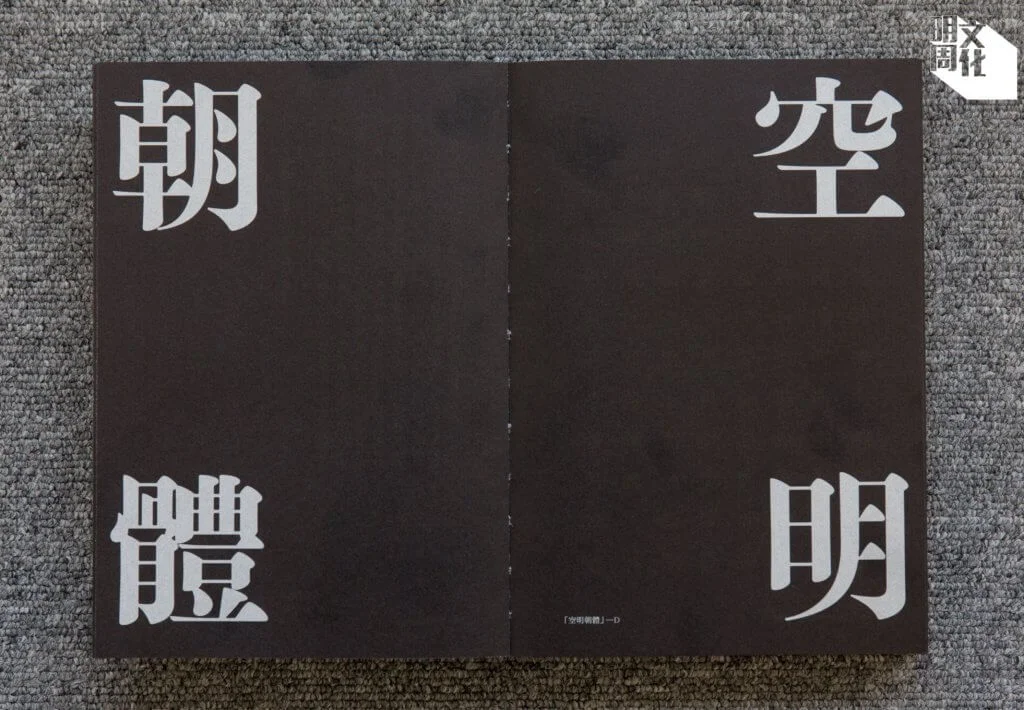
想見的改變正在發生
雖然排山倒海的實務壓力,讓許瀚文有點吃不消,但他很高興看見「空明朝體」及其美學廣獲認同,尤其是在台灣。近五千位贊助人中,八成多來自台灣,其中包括公共機構,如市政府、婦女基金會等;就連總統蔡英文的團隊,也採用了「空明朝體」就元宵節造圖,幫助推廣字體。
「好似可以慢慢改變到一些面貌。這其實頗符合自己的期待,就好似可以帶來新的改變,新的氛圍,符合到現世代華人喜歡的東西,或他們追求的價值觀,反映到時代對於字體而言很重要。」許瀚文當初想像「空明朝體」,就是想創造一套能夠貼近中文審美觀和時代氣氛的字體,讓使用繁體中文的地方,有耳目一新的閱讀感受。他的目標,似是在台灣漸漸成真。
香港造字仍然艱難
雖然這次眾籌募得五百多萬港元的資金,但許瀚文忠告,「接觸不少年輕人,都跟我講想做想試,但很多都捱不了多久,因為重複性太強,不是想像中那麼好玩。」說到底,字體設計就是日復日對着電腦一筆一劃砌字,是需要耐性堅持的乏味工作。「靠什麼維持?就是靠熱情,看你有多鍾意這件事。」發起眾籌前,從事字體設計十年的他,正處於事業瓶頸期,對自己前途迷惘,「『空明朝體』都係博一鋪,唔得我都諗住轉行。」
更何況,這在香港不是特別有利可圖的一行,「空明朝體」的贊助人中香港人僅佔5%。作為本地字體設計師,土生土長的地方關注度反而較低,許瀚文多少有點失望,但他也理解。「始終現在香港氛圍不是做投資、新的發展,很多事情都不穩定。」他續說,「這些文化發展事情,是安心的時候你才會想參與投資,但如果基本東西都不好,哪有心機去管這些東西?」
但許瀚文仍然期待在香港看見字體文化改變,不過他清楚,首要先做好「空明朝體」。待來年字體開發完成,他也會送給其他設計師前輩。「到他們用的時候,就會推動一些新的氣氛,因此想做好點,希望他們之後安心用到。」
許瀚文(Julius),字體設計師。二○○九年理工大學設計學院畢業後,跟從字體設計大師柯熾堅當學徒,其後任職英國Dalton Maag、美國Monotype等字體公司,曾為英特爾、《紐約時報》、《彭博商業周刊》機構等設計中文字型。參與開發字型逾十款。自二○一四年起設計「空明朝體」,今年初發起眾籌,募得逾二千萬台幣。